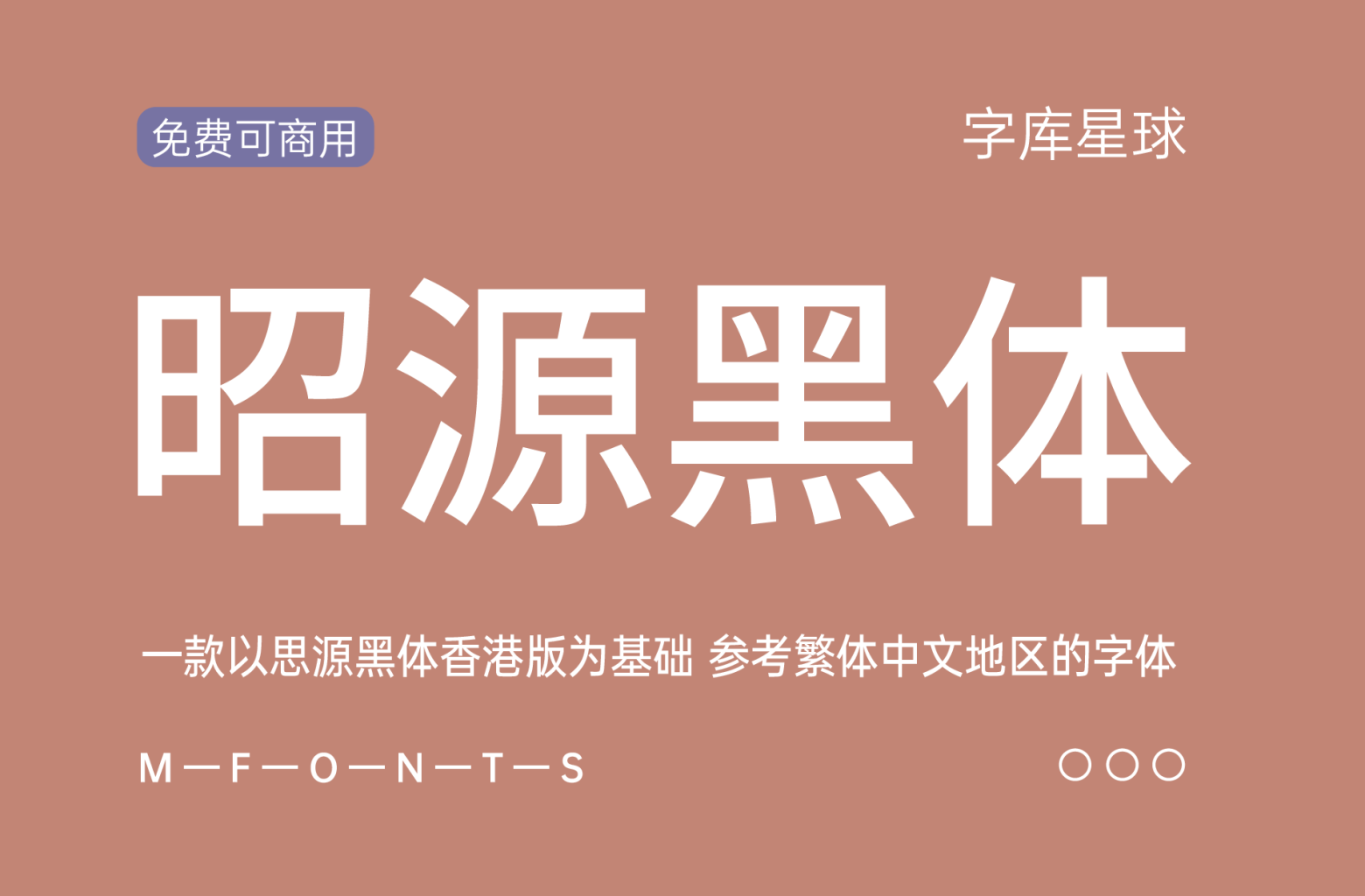
昭源黑体
现代笔形,兼顾印刷体架构
昭源黑体是一款以思源黑体香港版为基础,参考繁体中文地区的商用字体作出修改的免费可商用字体,目标是提供一个正体中文标准、地区中立、采用现代笔形风格而兼顾标准字形和印刷体架构的开源字体方案。
昭源黑体
收字繁多,香港字支援充足
昭源字体完整保留思源字体的字码支援,除了繁体中文会用到的Big5 和HKSCS 字集,其他如日本专用的和制汉字(例如「𩸽」、「峠」)亦不缺,日语假名、韩国谚文等也一应俱全。昭源字体更收有思源字体没有的新造字,包括2021 年纳入《香港增补字符集》补编的「𫬷」、「𭉝」。
昭源黑体
字重丰富,另有斜体、Text 家族分支
每款字体均备有8 款粗幼,更有能精确地控制字形粗幼(粗细)的可变式字型(Variable Font) 格式。昭源字体还提供更适用于内文印刷的Text 家族分支和英数字元来自真正斜体而非由机械产生的Italic 斜体配置。